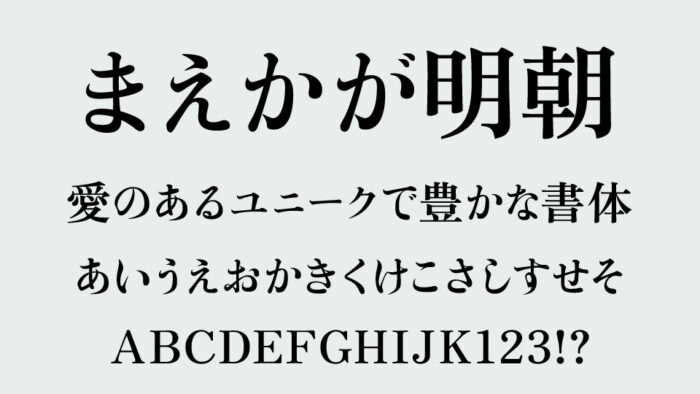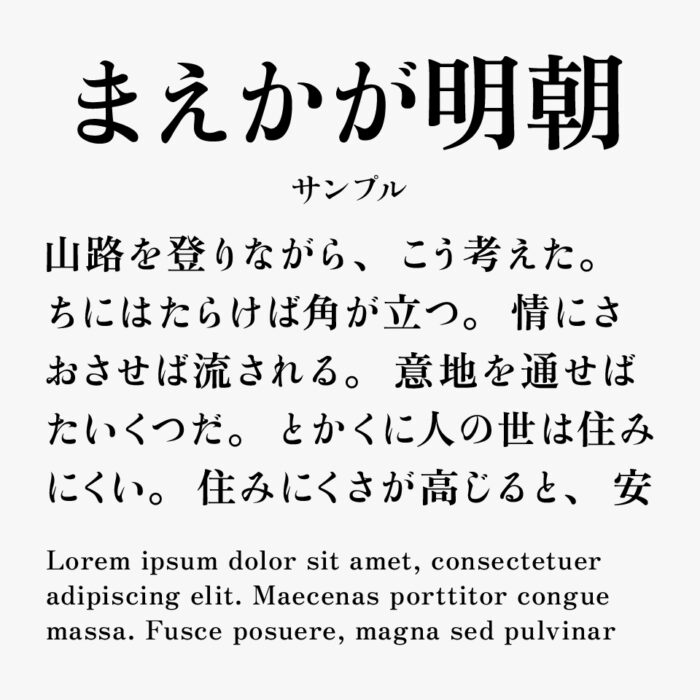
まえかが明朝
まえかが明朝フォントは、「もじくみ仮名」と「ZENオールド明朝」が混色された明朝体フォントです。
ひらがなには、レトロな風合いが素敵なレトロな明朝「もじくみ仮名」が使われており、漢字に「ZENオールド明朝」が使用されています。
オールドな雰囲気がとっても素敵で、フォント名のネーミングも面白いですね。